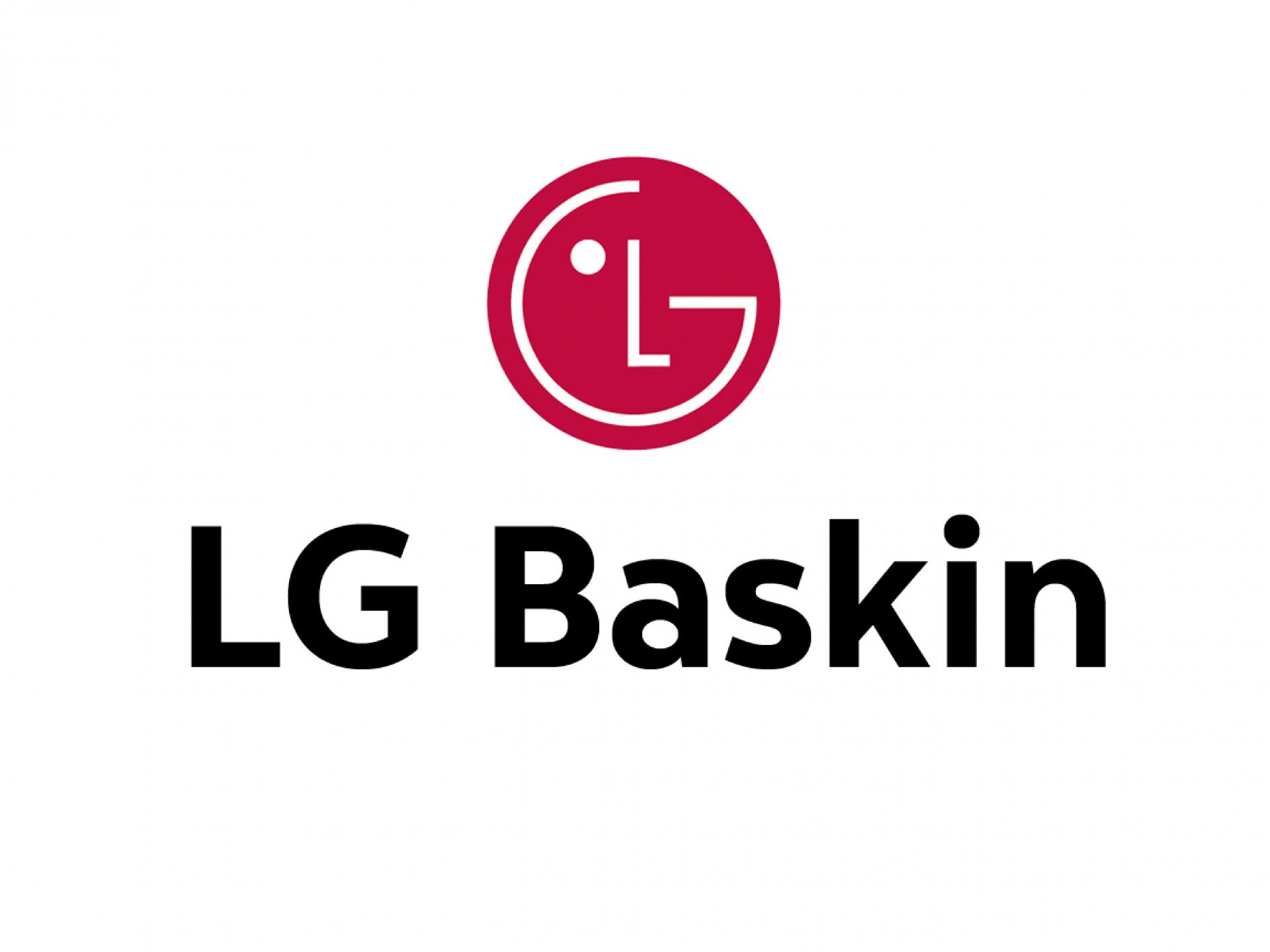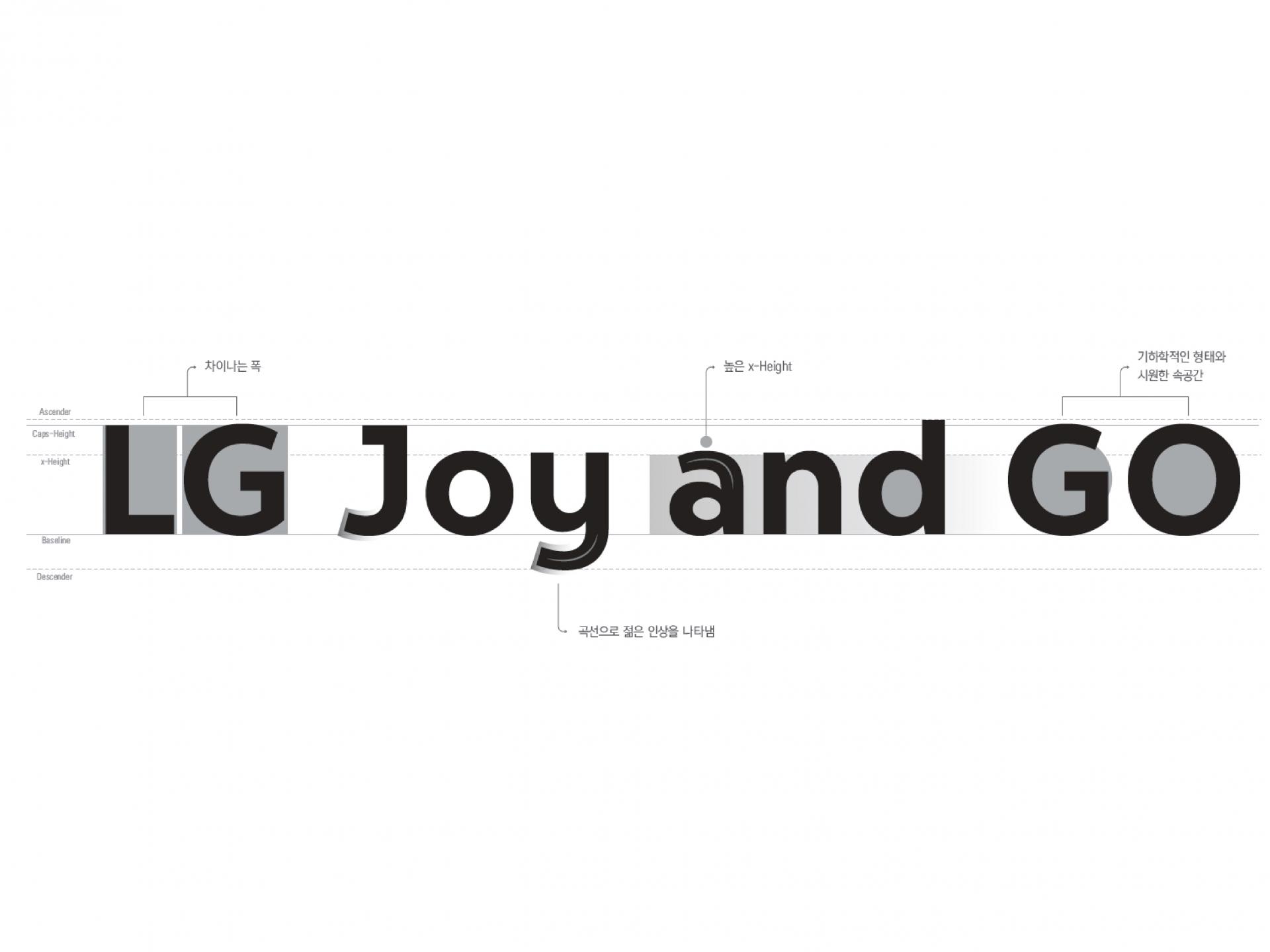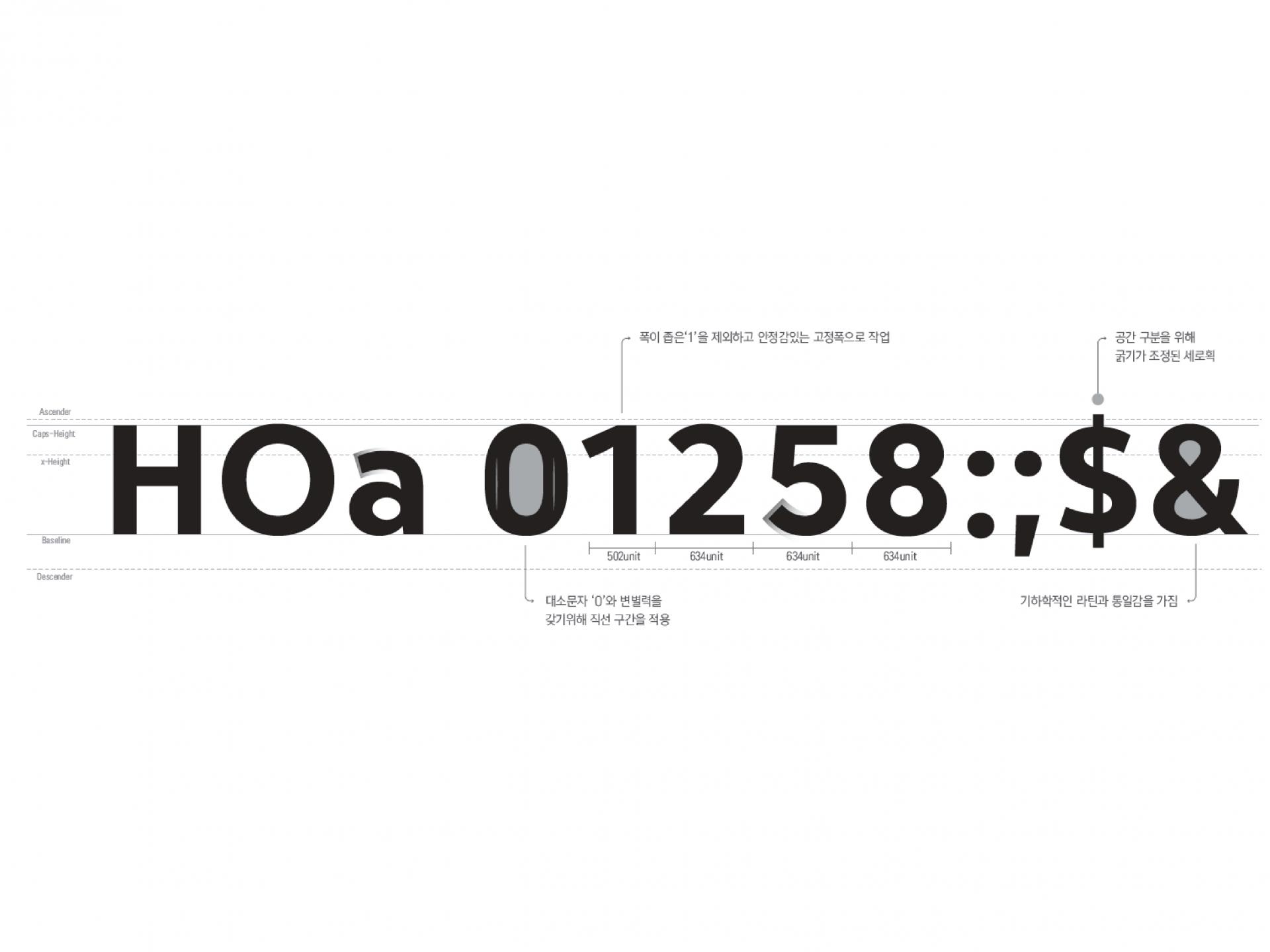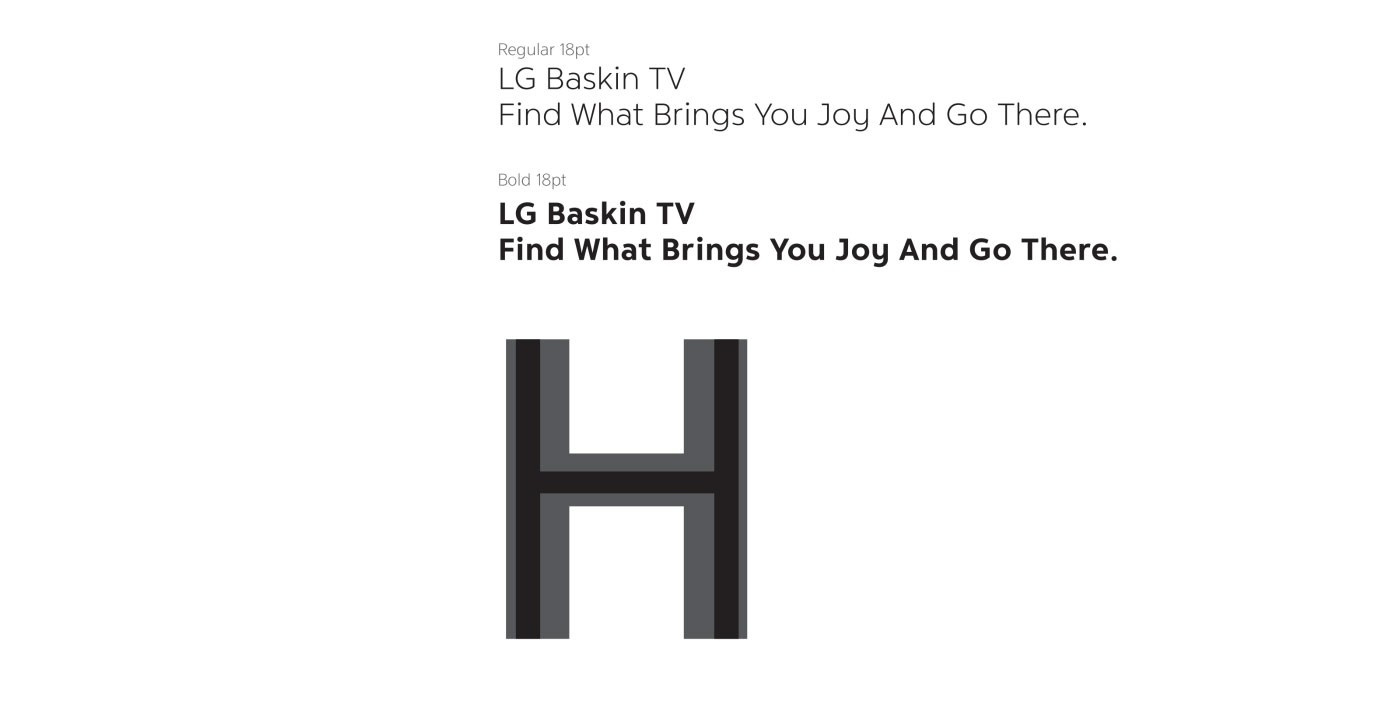
LG전자 [LG Bakin TV]
LG전자 [LG Baskin TV]
Geometric한 구조가 특징이며, 소문자 'a, g, y'등에서 곡선의 유연함으로 젊은 인상을 나타냈다. 대문자간의 폭 차이, 높은 x-height 등 기하학적인 구조 속에서 원형의 크고 시원한 속 공간이 특징이다.